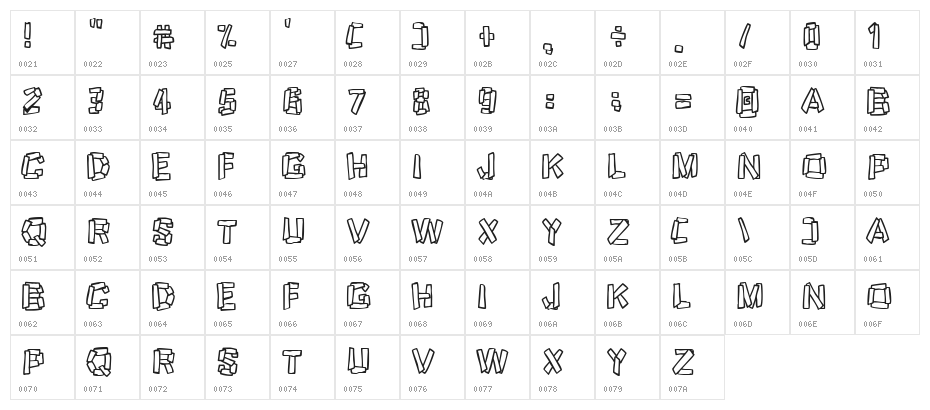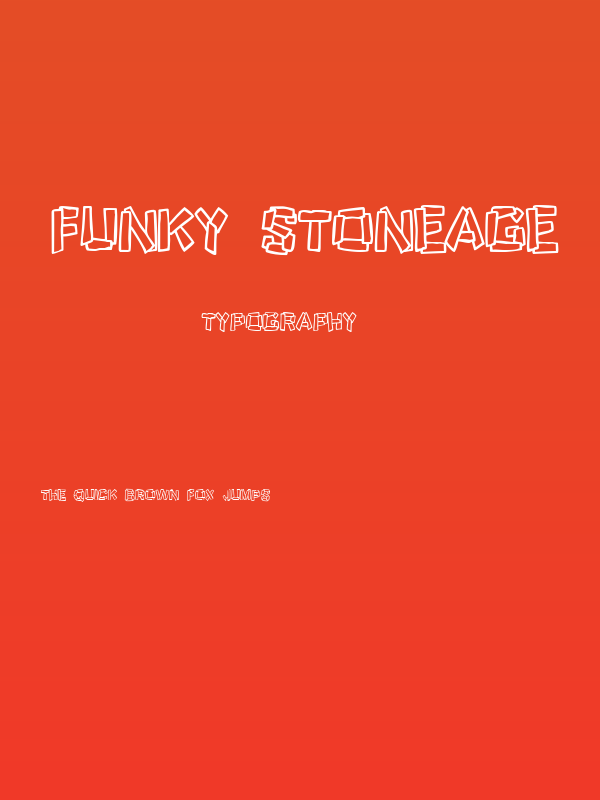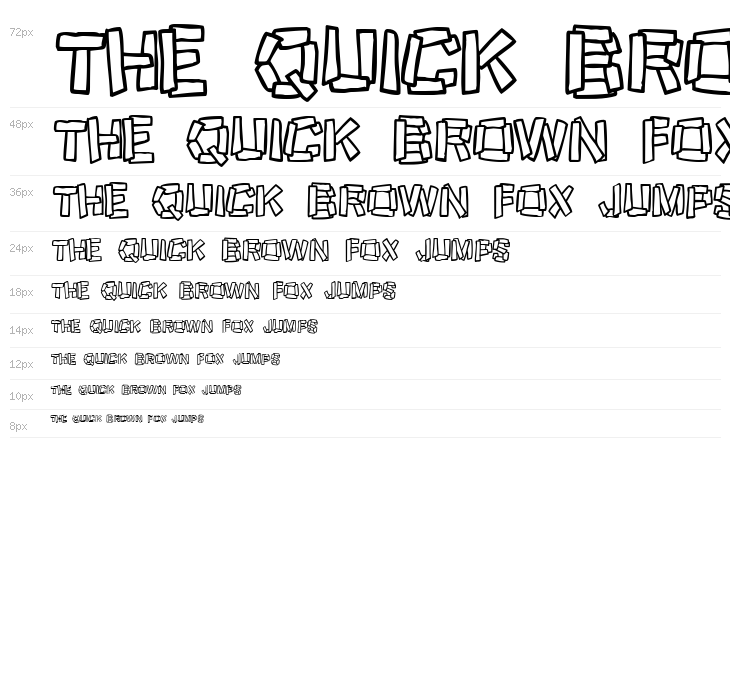
Funky Stoneage Font
✎ Outline
| Vorgeschlagene Projekte | Ideal for children's book covers, playful posters, themed party invitations, or any project needing a fun and quirky touch. |